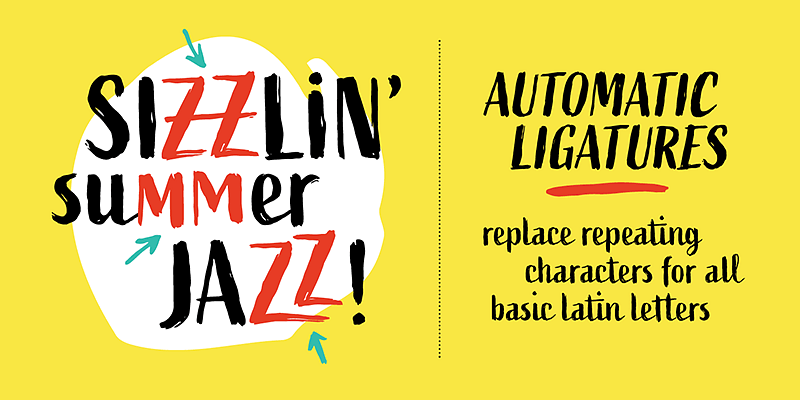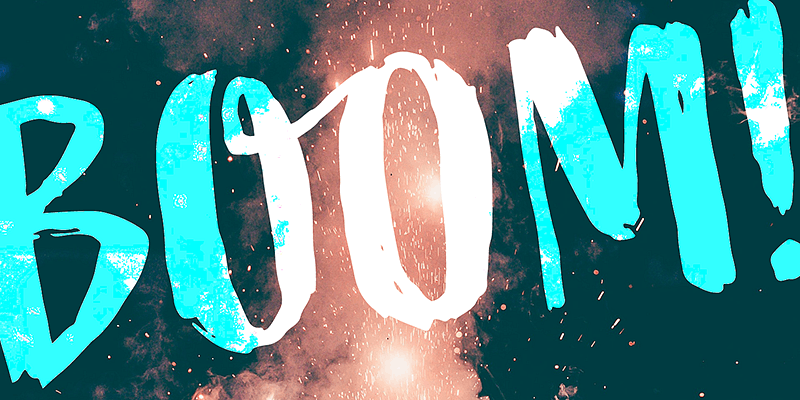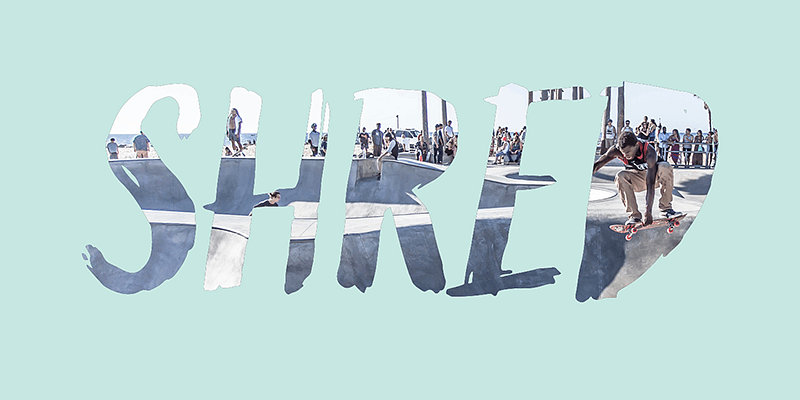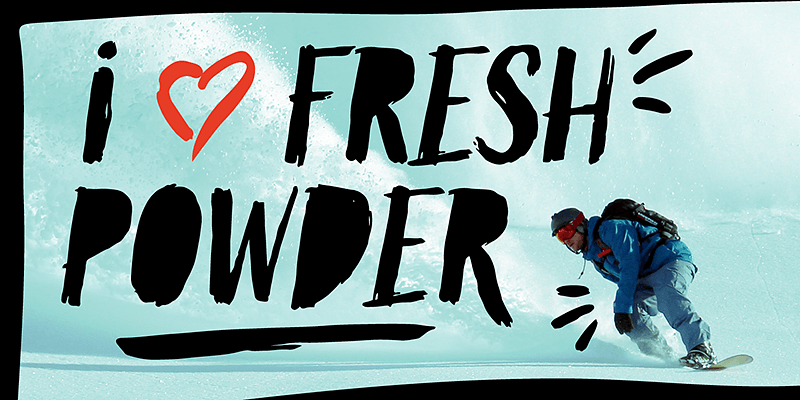
Active ist eine handgezeichnete Schrift mit Pinsel und Tinte. Sie ist selbstbewusst und gleichzeitig ausdrucksstark und hat ein strukturiertes Erscheinungsbild. Die leicht verkürzten Proportionen lassen sie ein wenig höher stehen.
Adam Ladd legt den Schwerpunkt auf Schriften, die nützlich und einzigartig sein sollen, und gestaltet Schriften von ganz unterschiedlicher Anziehungskraft – von moderner bis Vintage-Ästhetik; von serifenlosen und Serifenschriften bis hin zu Schreibschriften. Seine Erfahrung als Art Director bei zwei der angesehensten Design-Publikationen – den Zeitschriften HOW und PRINT – fließt in seine Arbeit als Schrift-Designer ein. Private Kunden und große Unternehmen in vielen Branchen haben seine Schriften lizenziert, darunter Disney, Whole Foods, Blizzard Entertainment und Penguin Random House.